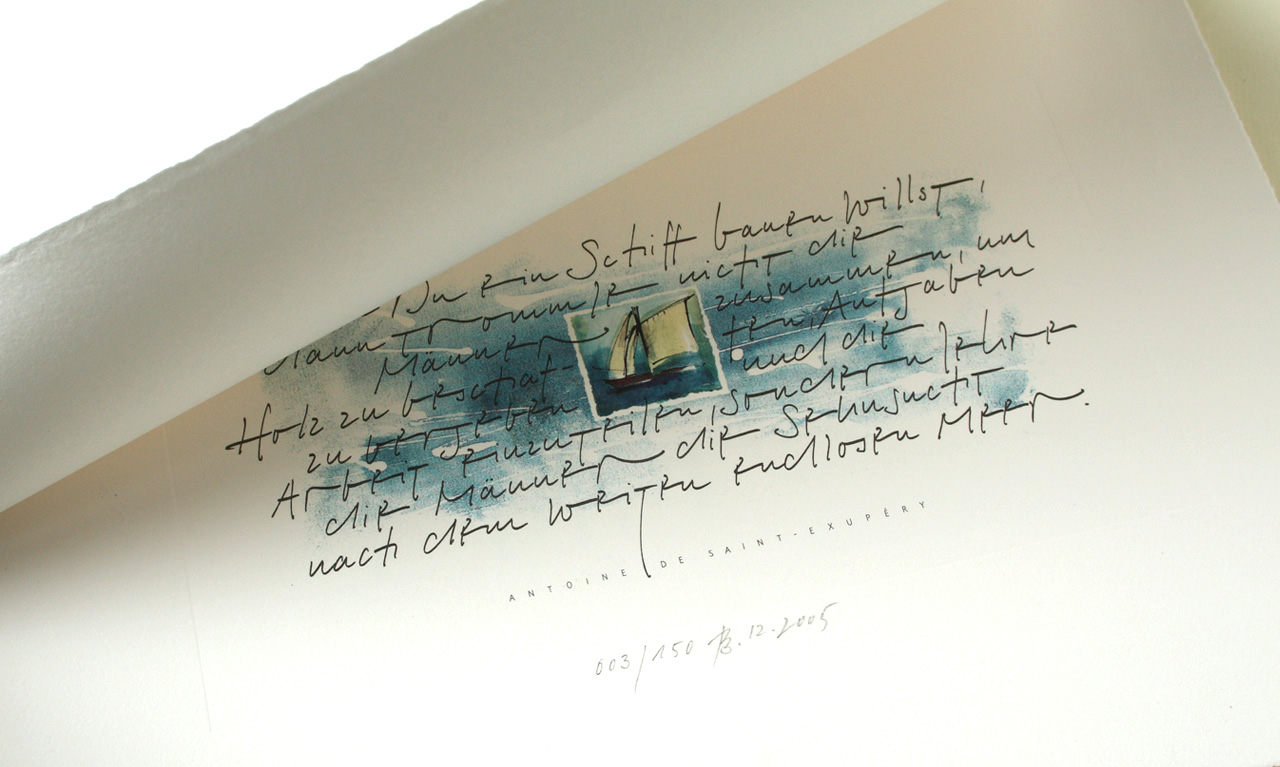
Weihnachtsedition, Druckgrafik
Designkonzeption, Zitatrecherche, Illustration, Kalligrafie, Produktionsabwicklung, Nummerierung und Signierung der limitierten Auflage.
Die Druckgrafik wurde auf Büttenpapier mit vierseitigem Büttenrand gedruck.
Zur Schrift: Die Schrift ist eine freie Interpretation der Römischen Kursiv (ca. 7. Jahrhundert). Nachdem ich mich in diese Schriftform eingeschrieben habe, bis die Hand sich an die typische Formensprache gewöhnt hat, habe ich Elemente meiner eigenen Handschrift einfließen lassen. Geschrieben ist der Text mit dem alten Schulfüllhalter meines Vaters.
Zur Produktion: Mappe und Druckgrafik wurden im Offsetdruck auf Büttenpapier gedruckt und geprägt. Beim Blatt der Druckgrafik wurde alle vier Seiten nach den Druck manuell gerissen, so dass die Anmutung eines vierseitigen Büttenrands entstand.